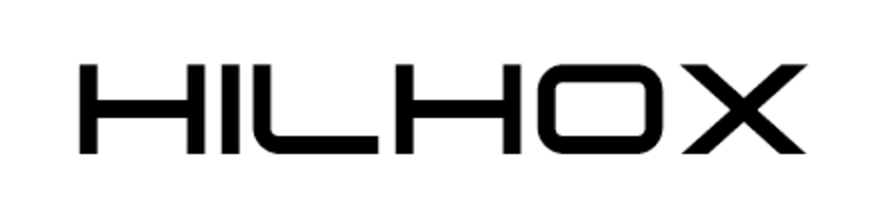
Brotschrift zu Tachyon Regular gesucht
ich suche eine Brotschrift zum Font "Tachyon Regular". Worum gehts? Nachstehend ein Firmenlogo, das in dem Font gehalten ist (Farben sind anders). Nun brauche ich eine Schrift, die hier dazu passt: für Mengentext, Überschriften etc. Ich selbst bin Laie und habe nur zwei Gedanken dazu, aber euch fällt bestimmt etwas ein:
1. da es sich um Technik-Branche handelt, sollte es wohl eher ein serifenloser Font sein (kein Dogma, aber wsl eher passend)
2. da die "Tachyon Regular" sehr "massiv" ist und auch schlecht in eine klassische Schriftkategorie mMn passt, ist wohl am ehesten eine Schrift "passend", die einen gewissen Kontrast bildet
Am liebsten wäre mir ein freier Font zB aus dem Google Font-Projekt. Oder aber einfach Beispiele für Schriften/Kategorien die überhaupt dazupassen würden. Danke für eure Hilfe!
Die Monda, Jura, Raleway oder die Roboto würden ganz gut dazu passen.
Die Abel würde aber auch einen schönen Kontrast, vor allem in der Breite, bilden.
Die Monda find ich dabei am Spannendsten, da sie zusätzlich zu ihrer Schlichtheit außerdem noch noch einen Kontrast zur  Tachyon Regular bildet. Auch die Jura finde ich sehr passend.